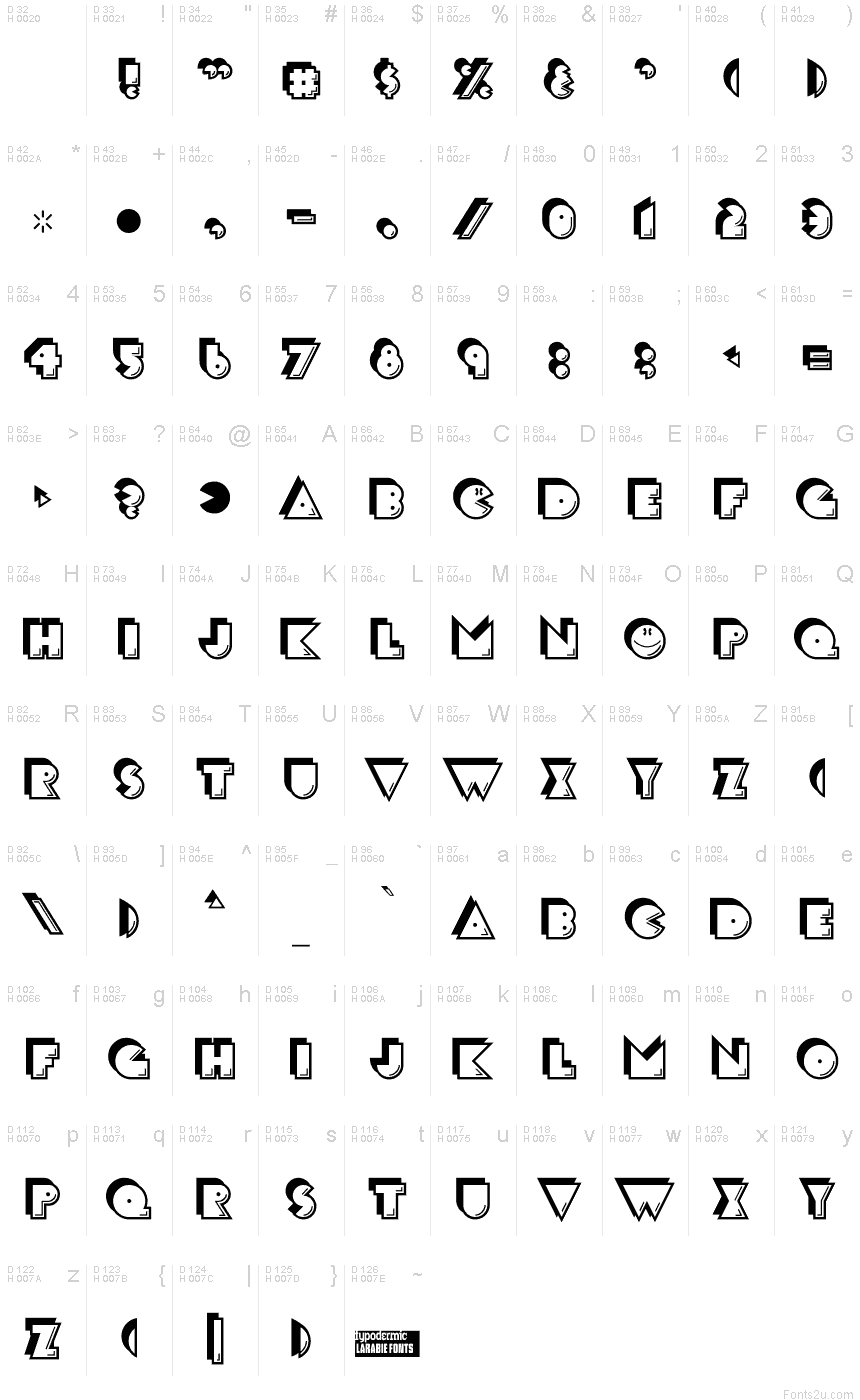
CrackMan di Ray Larabie è un font display in stile cartoon gratuito che trasforma ogni parola in un piccolo schermo arcade. I contorni neri corposi, i cerchi con i morsi e le forme triangolari a "fantasma" conferiscono alle lettere un movimento giocoso e vorace, come testo nel bel mezzo di una partita. Le forme appaiono solide e materiche, abbastanza spesse da risaltare su sfondi movimentati pur rimanendo leggibili a colpo d'occhio.
Con CrackMan puoi infondere immediatamente un'estetica retro-gaming in poster, volantini, grafiche per Twitch o YouTube, loghi di app, adesivi o inviti per feste di compleanno. Questo font gratuito prende vita soprattutto nelle dimensioni grandi, dove i dettagli dei caratteri possono risplendere; abbinalo a un carattere sans serif pulito e neutro per qualsiasi testo di supporto, in modo che il titolo rimanga il protagonista assoluto.